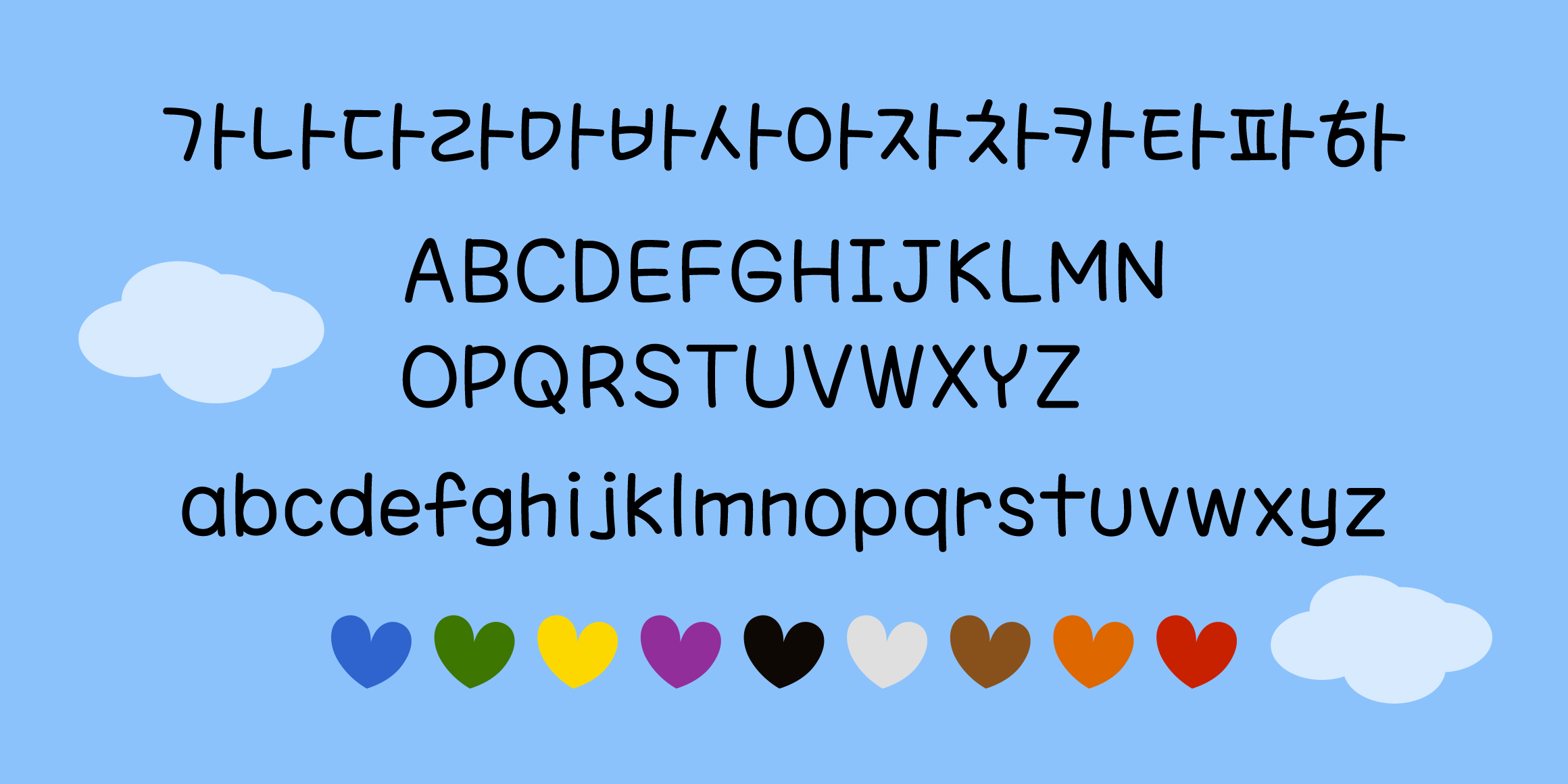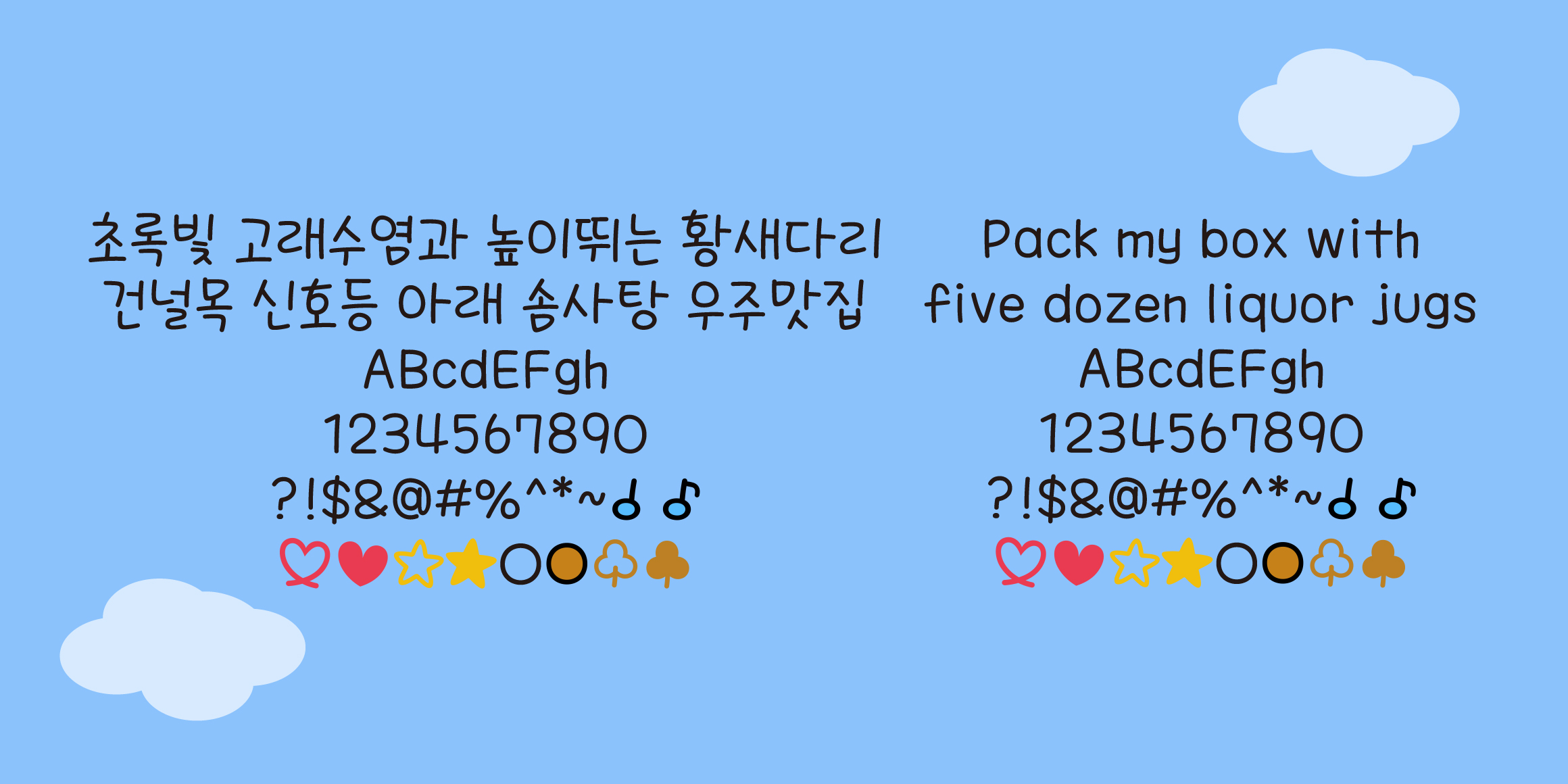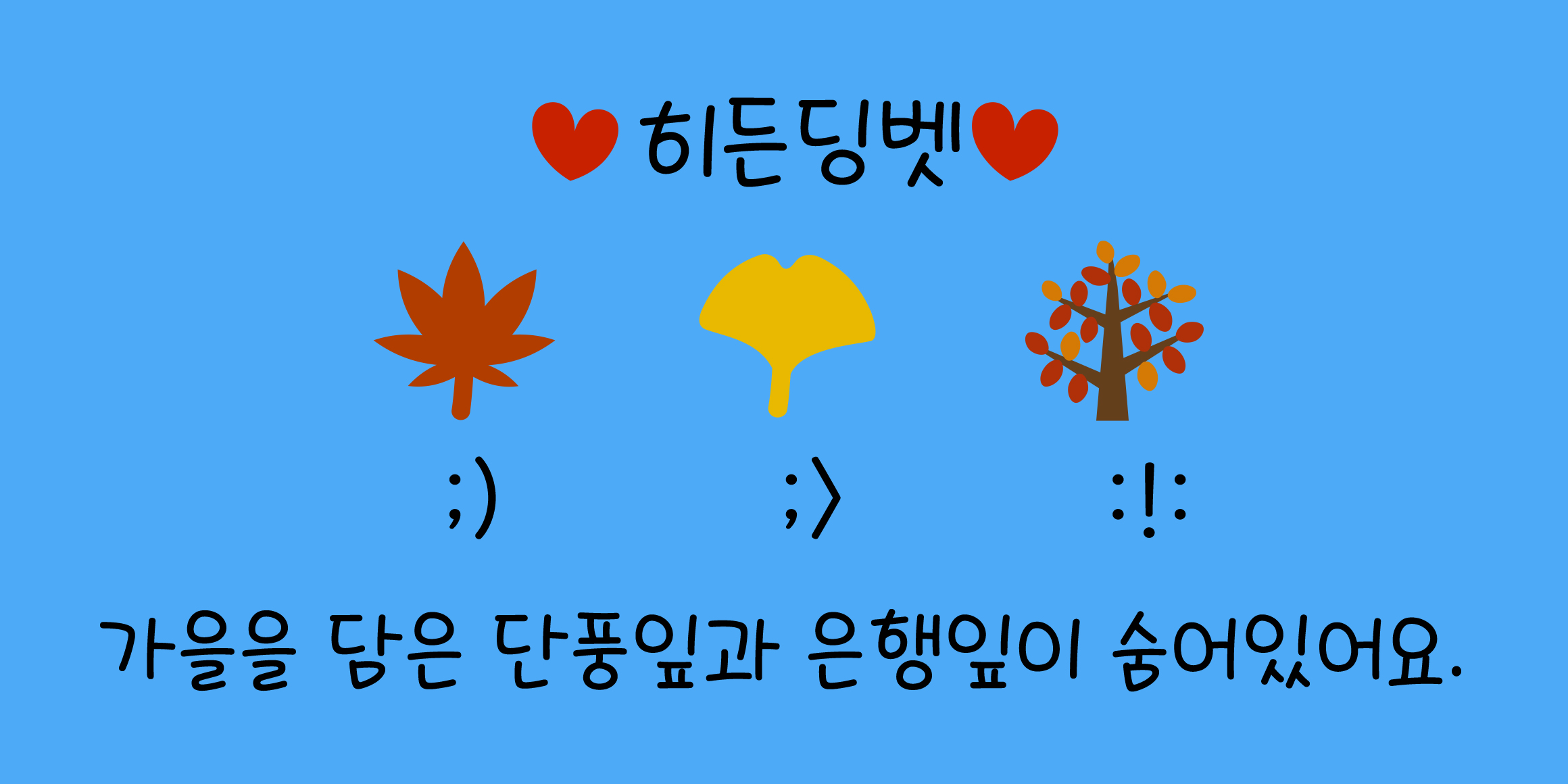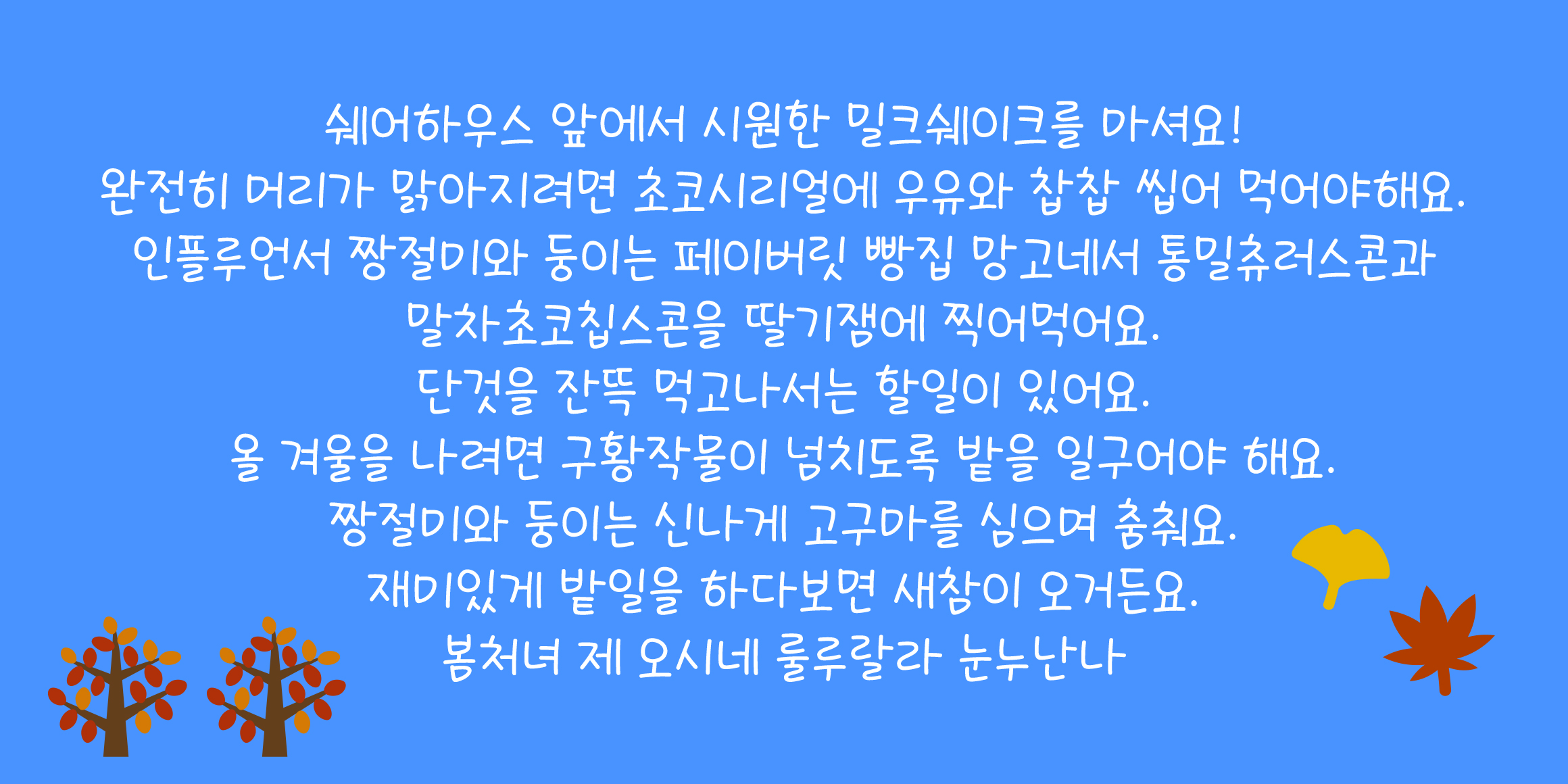
DX가을하늘
분류 Script,손글씨
'ㄹ,ㅁ,ㅂ,ㅎ'등의 자음에서 특징이 있으며, 단정하면서도 개성이 돋보이는 서체입니다!
글자가 큼직해서 가독성이 좋고,
오른쪽으로 살짝 기울어져 있는 빠르게 흘려쓰듯 한 손글씨입니다.
- ;) ;> :!: 총 3가지의 컬러히든딩벳이 숨어있답니다!
- 컬러 특수문자를 지원합니다.
- 단, 컬러 기능을 지원하지 않는 브라우저에서는 흑백으로 표기됩니다.
- 라틴, 일본어(히라가나, 가타카나), 키릴문자를 지원합니다.
• DX가을하늘 / DXAutumnsky